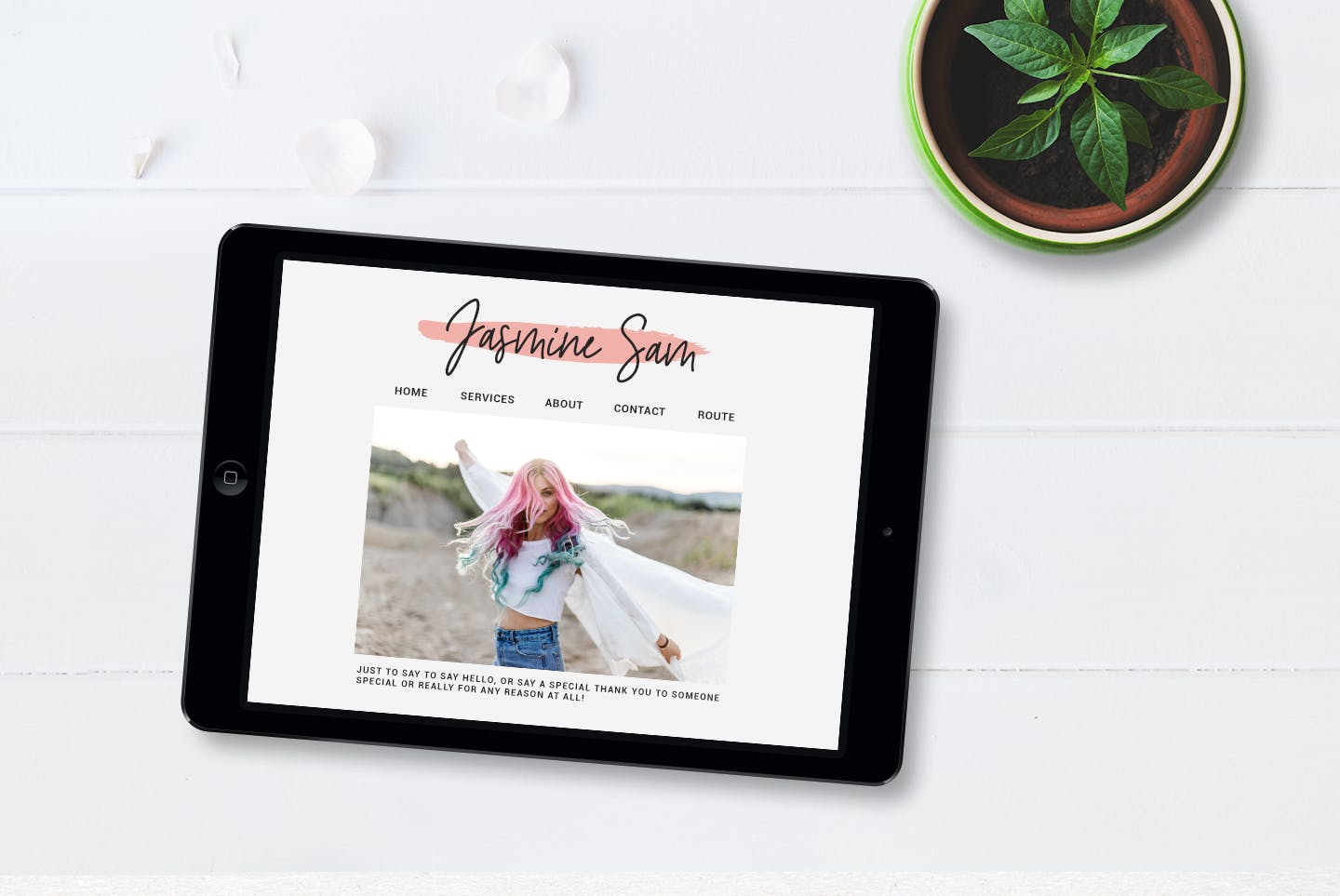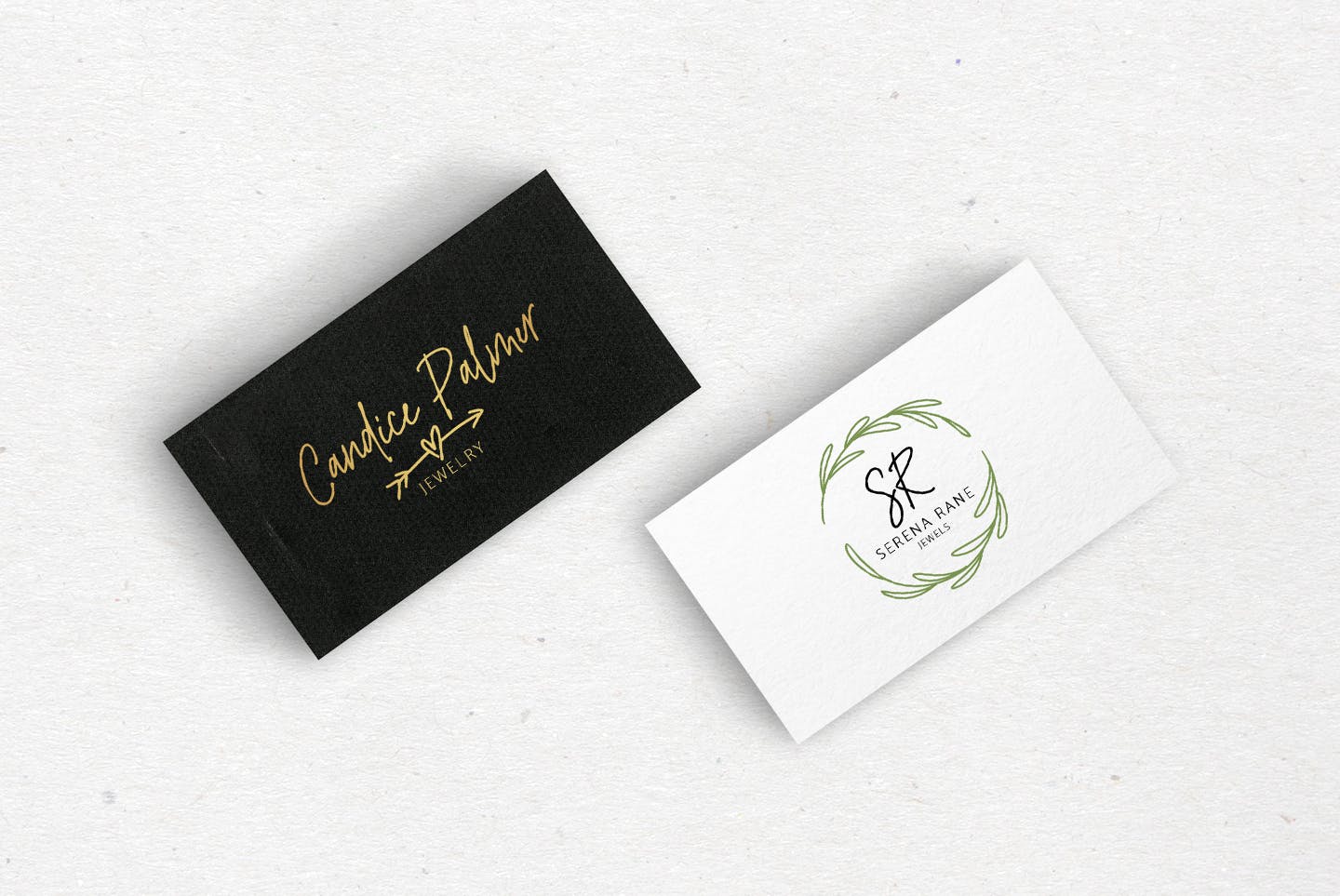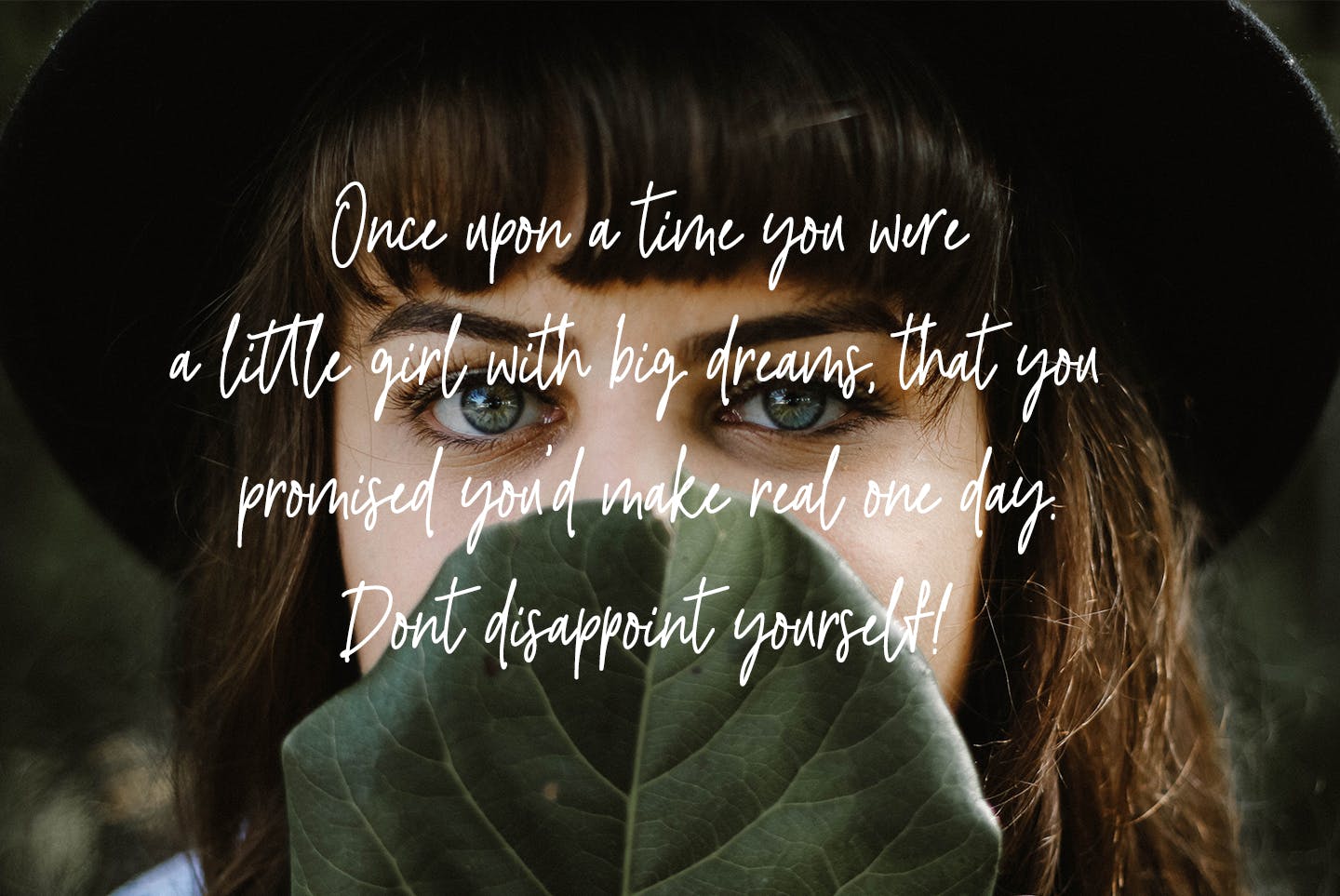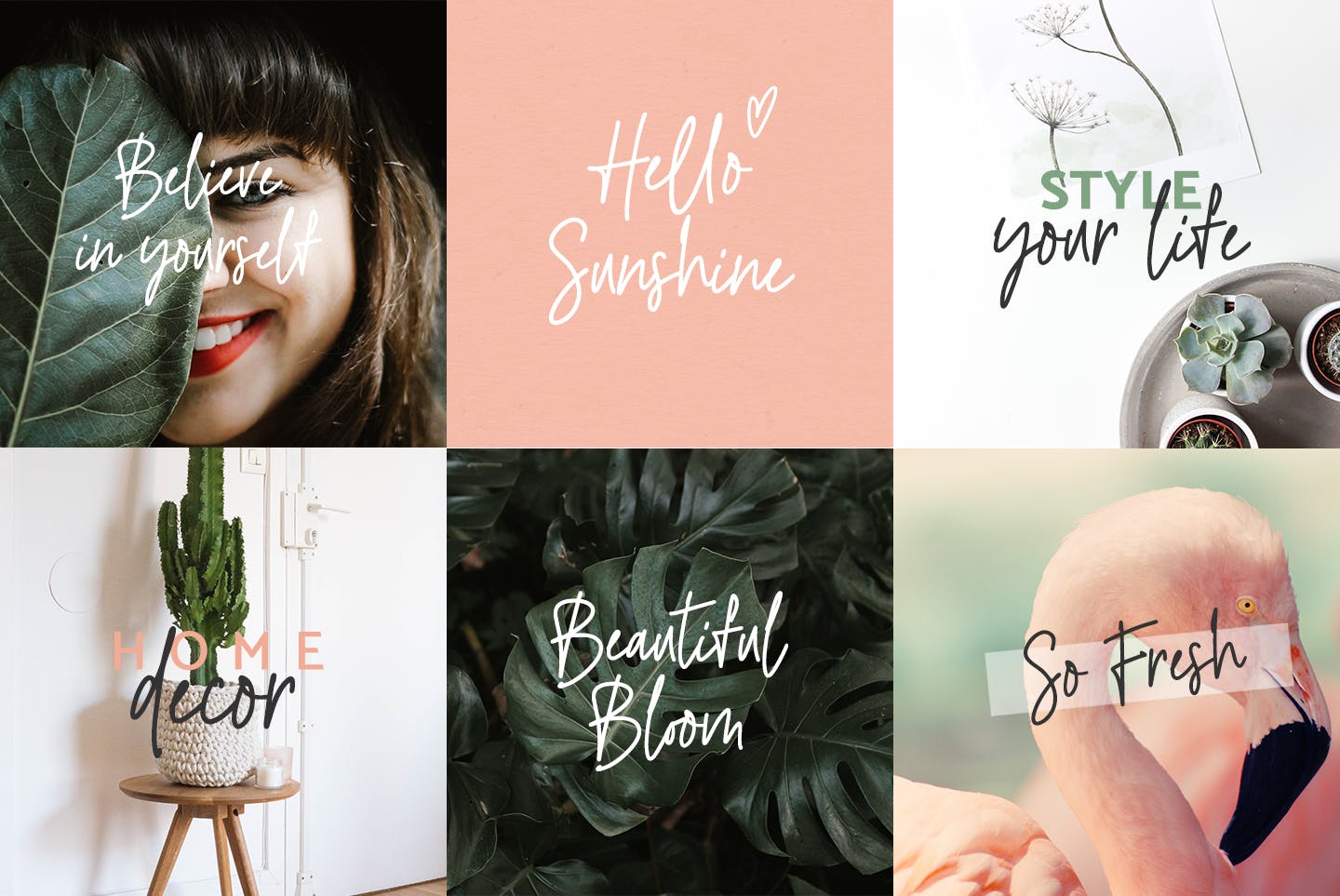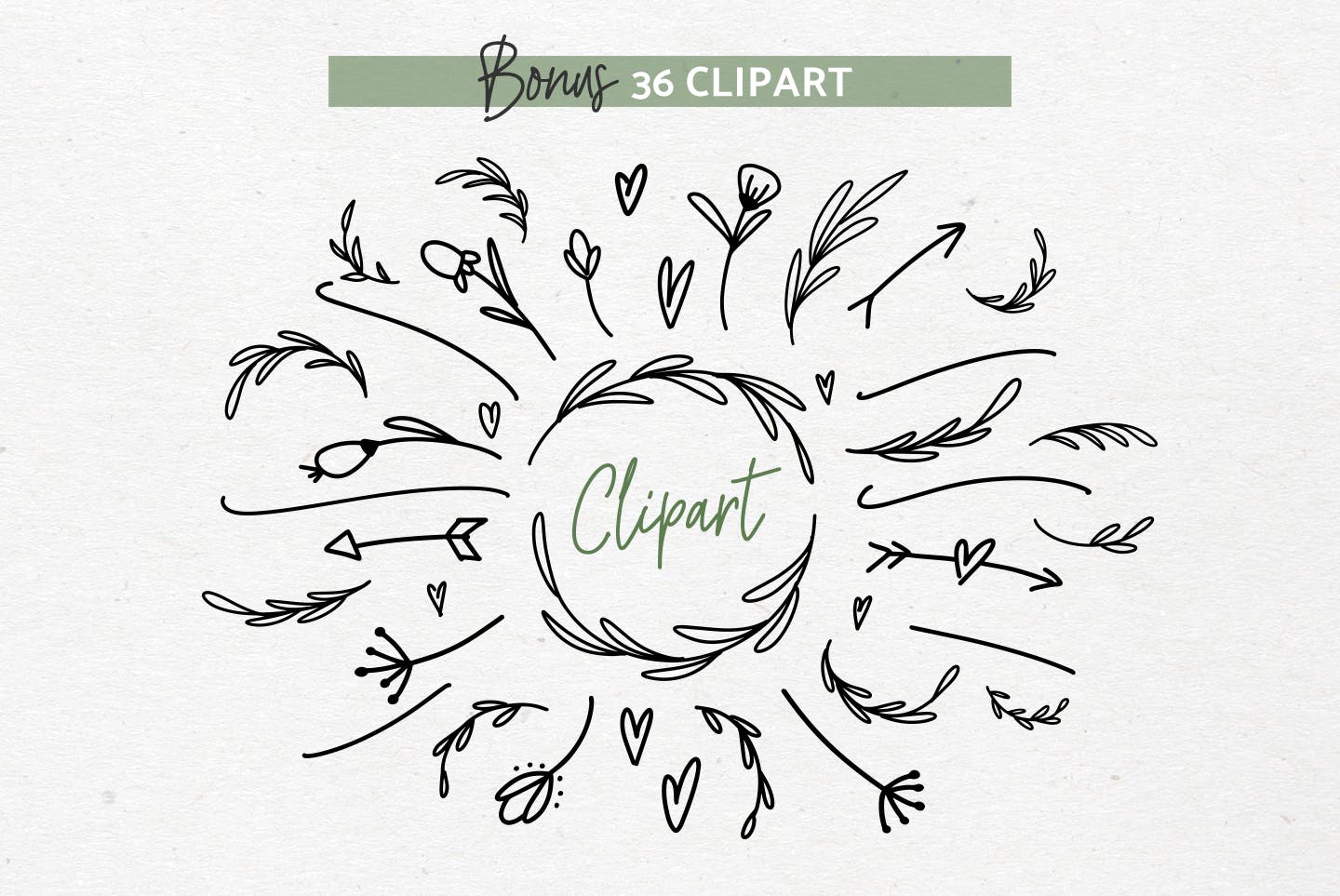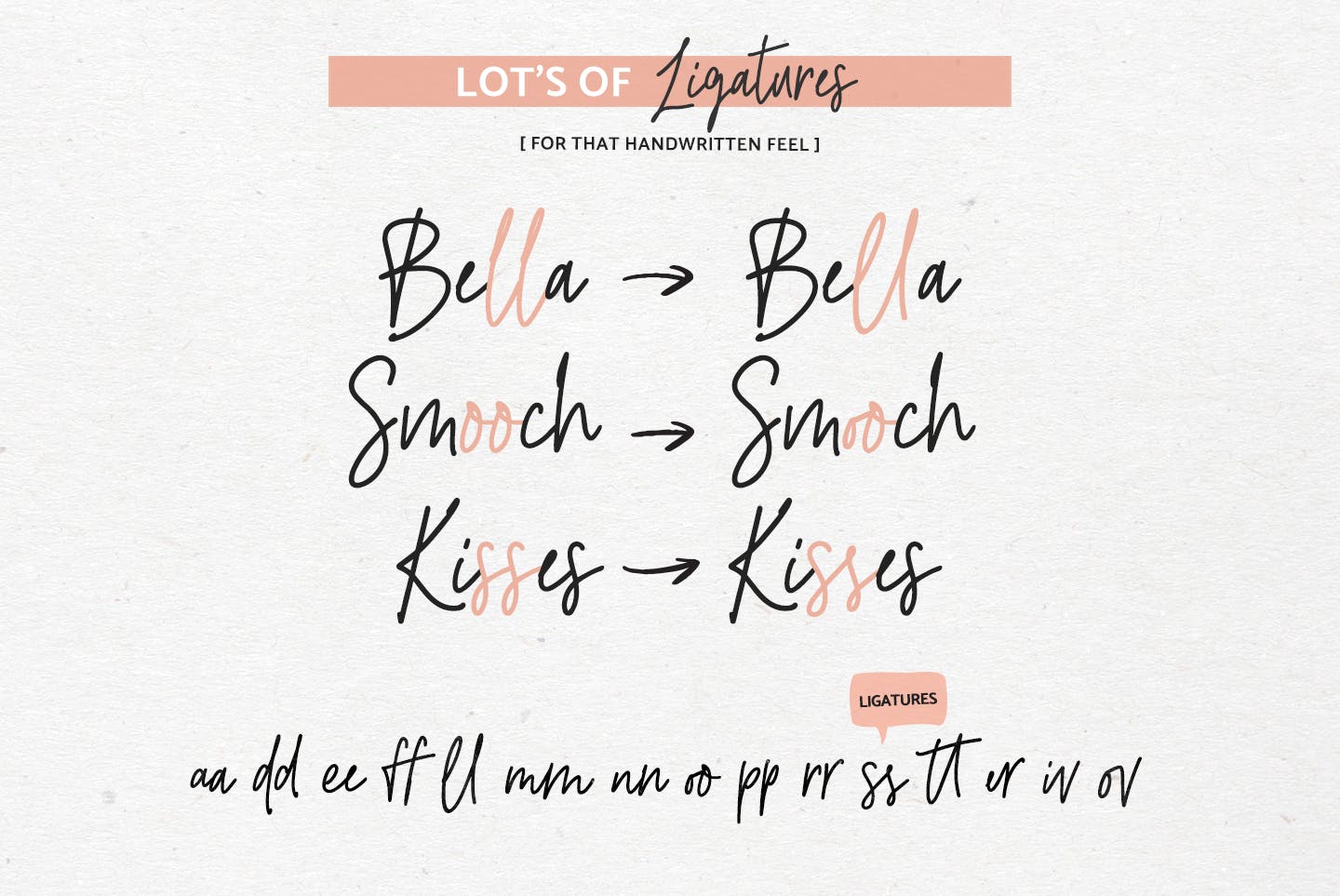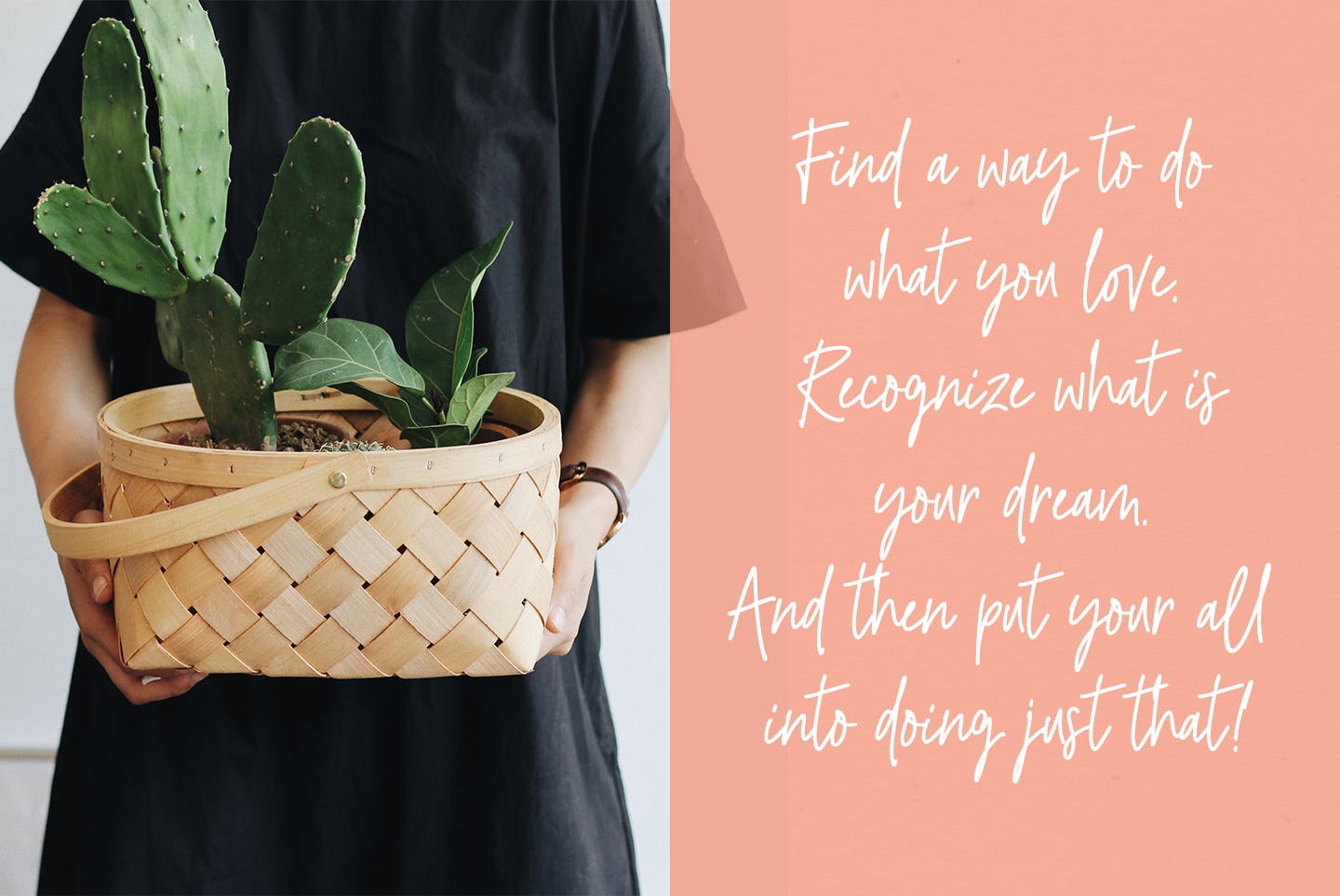
فونت River Jade همه چیزهایی که نیاز دارید را در یک بسته ارائه میدهد! این فونت امضای تازه با تعداد زیادی لیگاتور برای ایجاد حس دستنویس طراحی شده است. همچنین شامل ۶ قالب لوگو میباشد که به شما این امکان را میدهد تا در کمترین زمان لوگوهای حرفهای برای مشتریان خود طراحی کنید.
علاوه بر این، این بسته شامل کلیپ آرتهای اضافی است که طراحی را بسیار آسانتر و سرگرمکنندهتر میکند. از خلاقیت لذت ببرید!